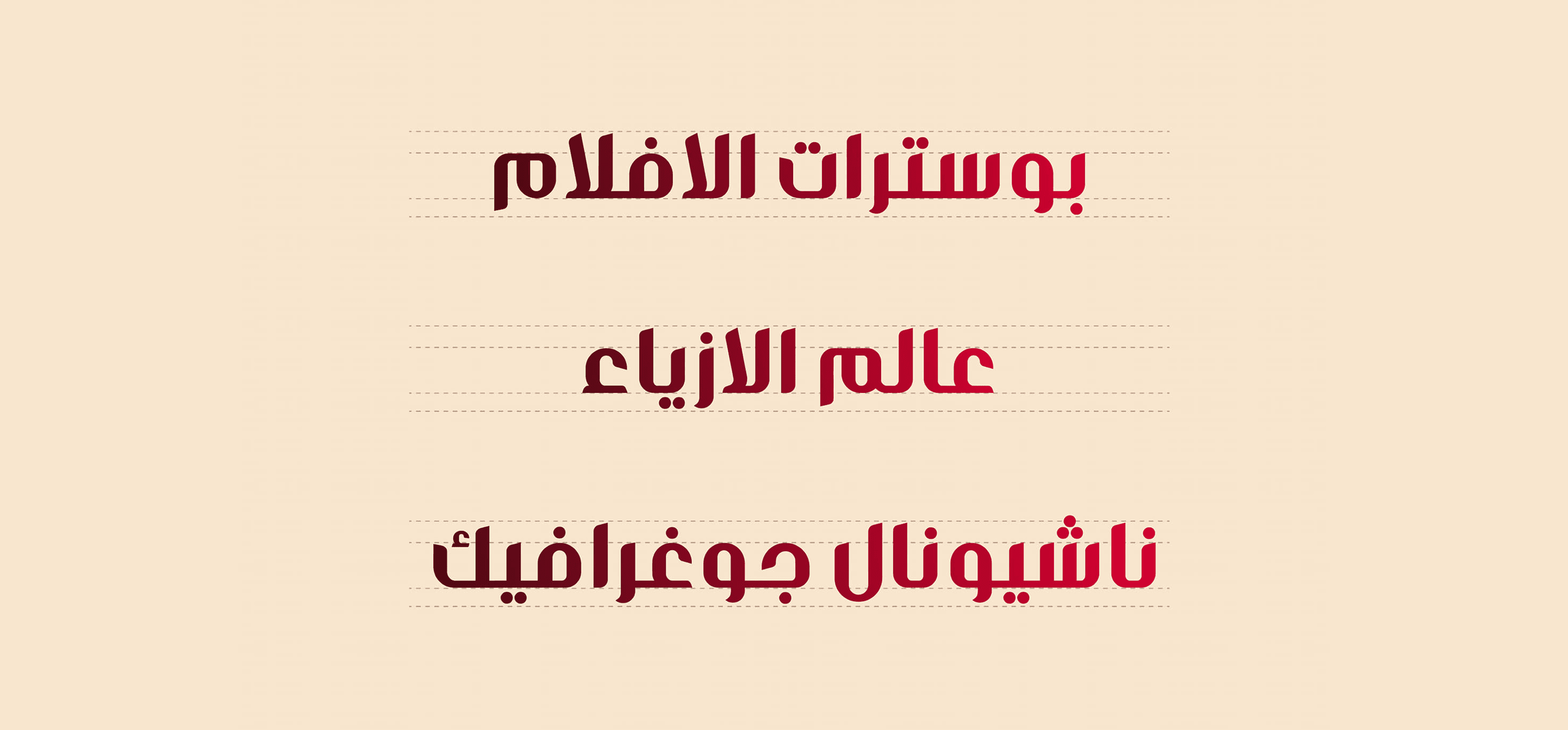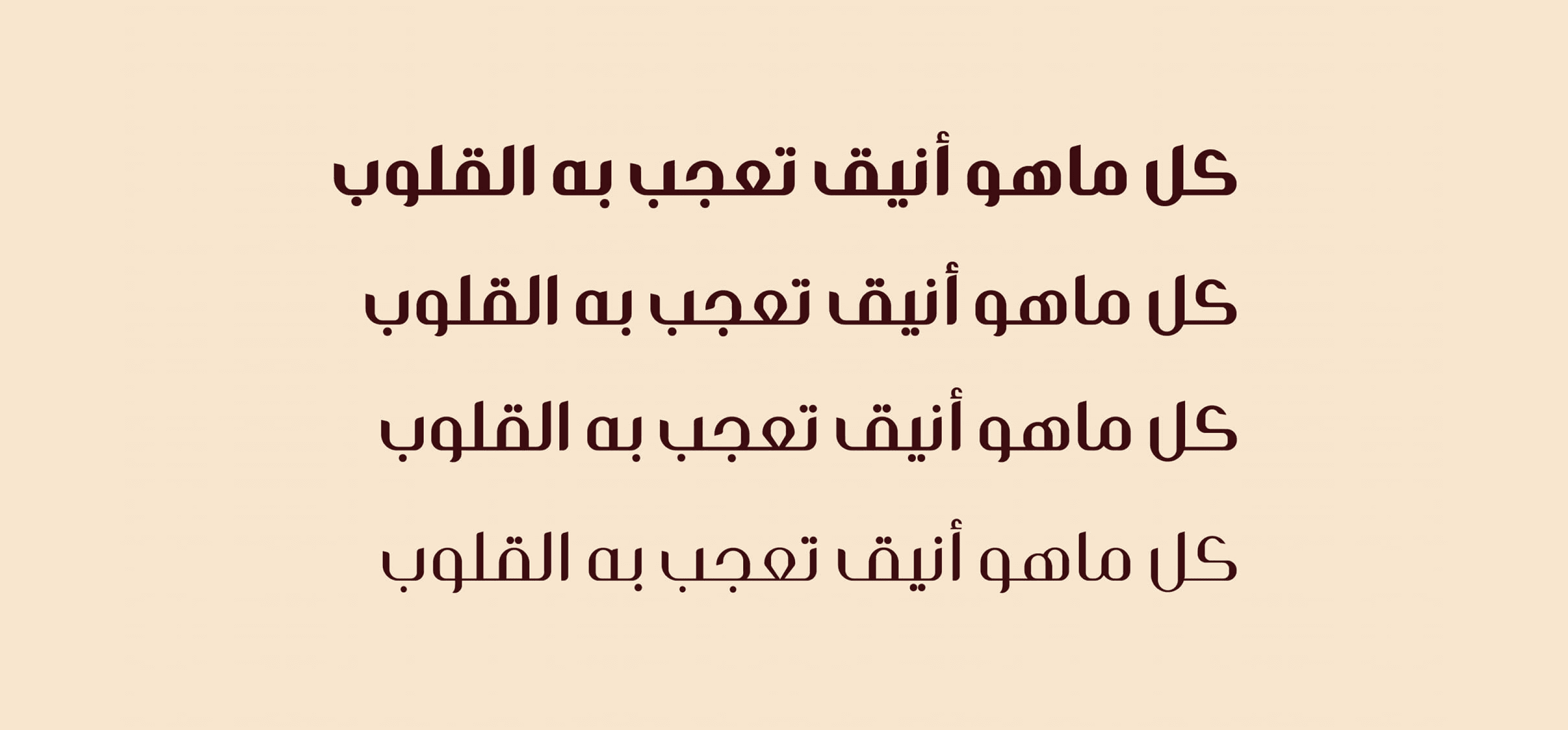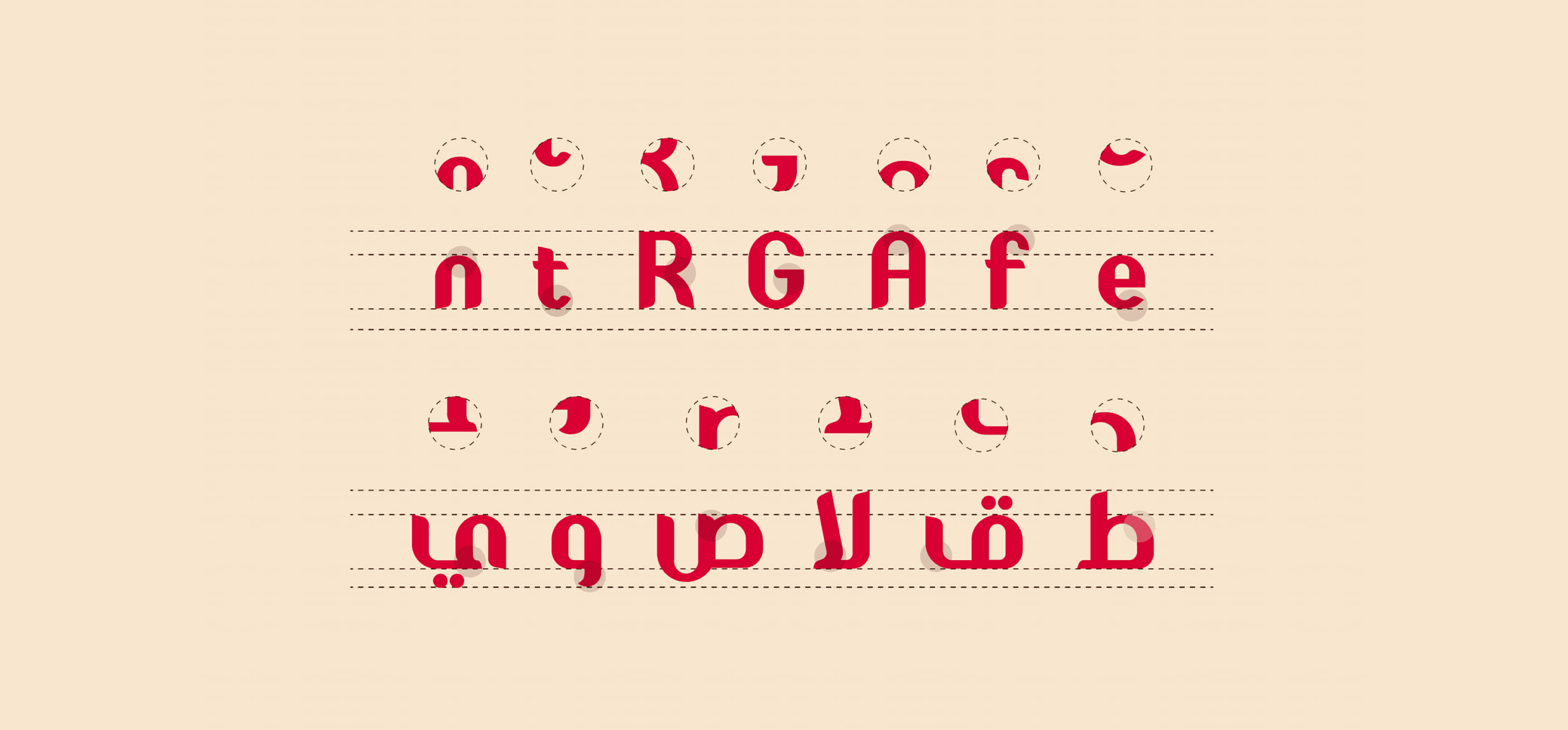
خط عربي وإنجليزي عصري، يتميّز بتصميمه الجذاب والواضح، مناسب للاستخدام في المجالات الإبداعية المختلفة مثل:
بوسترات الأفلام
عالم الأزياء
ناشيونال جيوغرافيك
الإعلانات والعناوين الجريئة